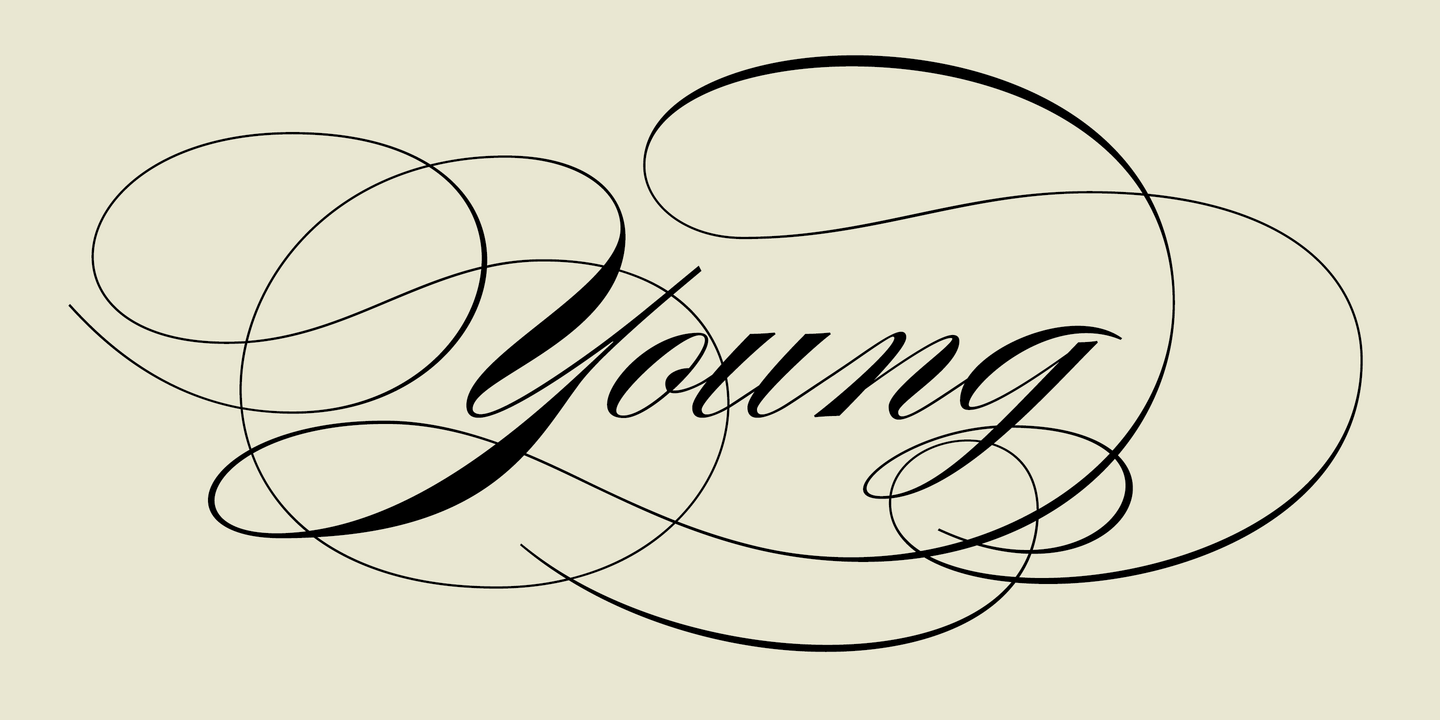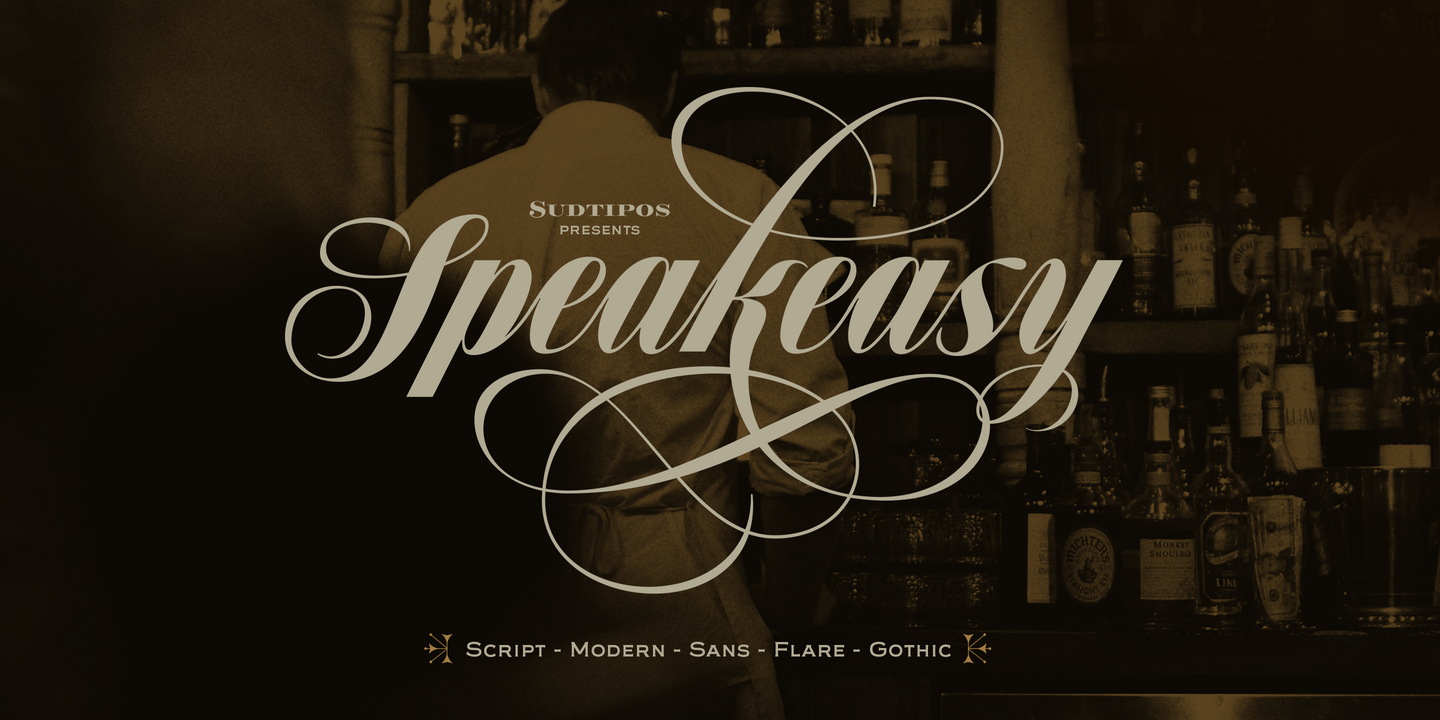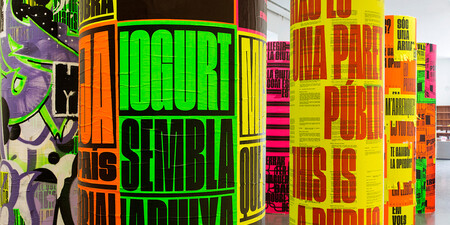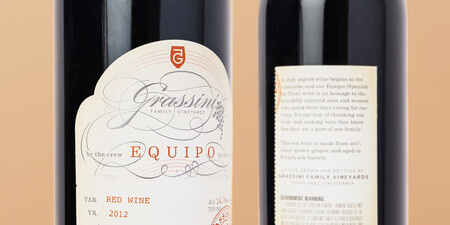
Fonts von Sudtipos
Sudtipos
Die Designer , aus denen sich Sudtipos zusammensetzt, kommen aus so unterschiedlichen Ländern wie Argentinien, Kolumbien, Spanien, Deutschland und Mexiko, um nur einige zu nennen. Die Vielfalt der Kulturen, der Geschlechter und der Ästhetik haben eine einzigartige Sammlung von Schriften geschaffen.
Auf der ständigen Suche nach neuen typografischen Nischen, die es zu erforschen gilt, und in dem ständigen Bestreben, mit den technologischen Fortschritten Schritt zu halten, ist Sudtipos seit 20 Jahren auf dem Markt und hat sich als eine der am meisten ausgezeichneten und verwendeten Schriften Foundrys in der Welt des Designs etabliert. Ihre Projekte reichen von exquisiter Typografie für Verpackungen bis hin zu komplexen typografischen Systemen für Texte. Sudtipos Schriften kennt keine Grenzen, denn seine Designer sind in der ganzen Welt verbreitet.
Alejandro Paul
Ale Paul ist einer der Gründer des Projekts Sudtipos und eine wichtige Referenz für die Qualität seiner Arbeit. Seine Arbeit hat wesentlich dazu beigetragen, Argentinien auf der Landkarte des Grafikdesigns zu verankern. Ales Karriere als Art Director führte ihn in einige der renommiertesten argentinischen Studios, wo er für so bekannte Marken wie Procter & Gamble, SC Johnson, Danone und andere arbeitete. Mit der Gründung von Sudtipos verlagerte Ale seine Bemühungen auf das Design von Schrift und entwarf Fonts, Schriftzüge und Werbeflächen für mehrere führende Verpackungsagenturen. Im Jahr 2012 wurde sein Font für Letter2 ausgewählt. Er erhielt vier Exzellenzzertifikate vom Type Directors Club NY und mehrere Auszeichnungen bei der Tipos Latinos Biennale für Typografie.
Er unterrichtet ein Postgraduiertenprogramm für Typografie an der Universität von Buenos Aires, wo er zuvor Grafikdesign unterrichtete. Außerdem hat er Seminare gehalten und auf den Konferenzen Type Master Weeks NY, TypoBerlin, TypeCon, Pecha Kucha und Atypi, im Type Directors Club in New York City sowie auf Veranstaltungen in Hongkong, Frankreich, Tschechien, Österreich, Spanien, Portugal, Chile, Brasilien, Kolumbien, Ecuador, Venezuela, Bolivien, Uruguay, Mexiko und Kanada gesprochen. Seine Arbeiten wurden in Publikationen rund um den Globus veröffentlicht, darunter Eye, Communication Arts Print, Creative Review, Visual, Creative Arts, Novum und viele andere. Er wurde zum Länderdelegierten von ATypi ernannt und ist Mitglied der Alliance Graphique Internationale - der ersten für Argentinien.